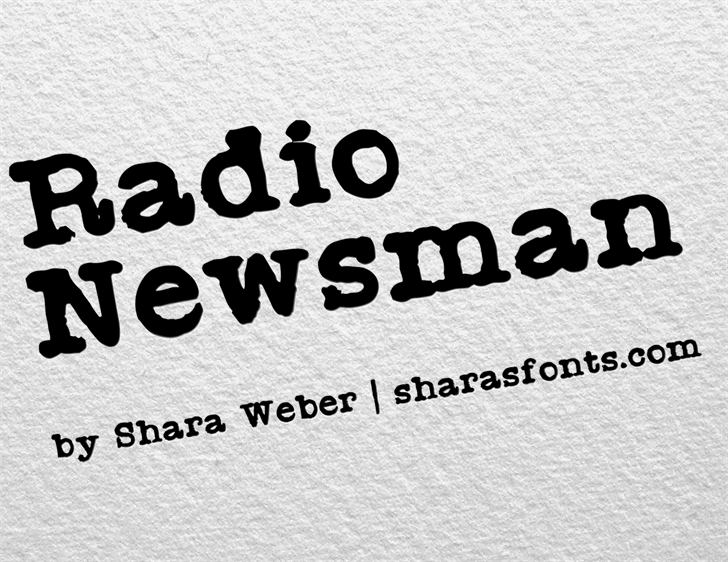
A Radio Newsman Font é uma elegante fonte serif que traz consigo um toque moderno e sofisticado. Suas linhas sóbrias e sutis criam um contraste perfeito com as letras mais elaboradas, fazendo-a adequada para design gráfico de alto padrão. Ideal para jornalismo digital, publicações de notícias ou qualquer aplicação que exige uma aparência profissional e respeitável, a Radio Newsman é uma escolha segura para quem procura um estilo serio e impecável. Desenvolvida pela Shara Weber, esta fonte oferece um refinamento que valoriza seus trabalhos, fazendo com que cada palavra seja percebida como um momento de design. É perfeita para criar textos informativos e respeitáveis, sem perder sua expressividade ou personalidade. A Radio Newsman é a escolha certa para quem busca uma fonte serif poderosa e elegante.
Designer: Shara Weber